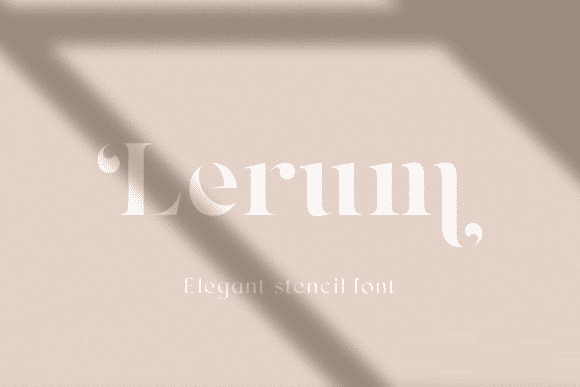
Lerum
- это элегантный и смелый шрифт с засечками.
Он выразителен и игрив, а благодаря гармоничному сочетанию символов и чередований этот шрифт заставит ваш продукт казаться привлекательным и дорогим.